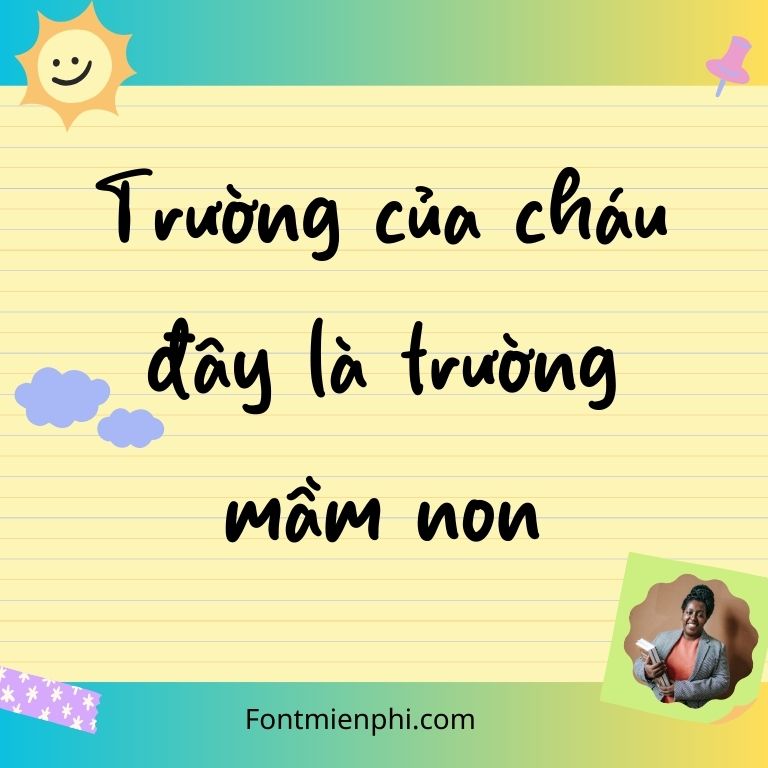
bộ Font Việt hóa VIP Burger Steak
Tải ngay bộ Font Việt hóa VIP Burger Steak siêu đẹp dành riêng cho dân thiết kế đồ họa. Đây là phông chữ hoàn hảo cho các dự án thiết kế logo, menu, và banner quảng cáo mảng F&B (ẩm thực, nhà hàng). Với đường nét mập mạp, vui nhộn và vô cùng cá tính, VIP Burger Steak đã được Việt hóa chuẩn xác, hỗ trợ gõ tiếng Việt có dấu đầy đủ không lỗi font. Khám phá và download miễn phí phông chữ độc đáo này để biến các thiết kế của bạn trở nên hấp dẫn, chuyên nghiệp và “ngon mắt” hơn
Khám Phá Sự Độc Đáo Của bộ Font Việt hóa VIP Burger Steak
Trong lĩnh vực thiết kế đồ họa, đặc biệt là mảng ẩm thực (F&B), việc lựa chọn đúng phông chữ đóng vai trò cực kỳ quan trọng trong việc kích thích vị giác và thu hút khách hàng. Nếu bạn đang tìm kiếm một kiểu chữ mang lại cảm giác ngon miệng, gần gũi và đầy sức sống, thì Font Việt hóa VIP Burger Steak chính là sự lựa chọn không thể bỏ qua.
1. Font VIP Burger Steak Là Gì?
VIP Burger Steak là một phông chữ hiển thị (display font) mang phong cách vui nhộn, mập mạp và đầy cá tính. Giống như tên gọi của mình, những đường nét của font chữ này gợi lên hình ảnh của những miếng bít tết dày dặn hay những chiếc burger đầy đặn, hấp dẫn. Nhận thấy tiềm năng ứng dụng to lớn của phông chữ này, các designer đã tiến hành Việt hóa hoàn chỉnh, giúp người dùng Việt Nam dễ dàng sáng tạo mà không lo lỗi dấu.
2. Ưu Điểm Nổi Bật Của Bản Việt Hóa
• Việt hóa chuẩn xác: Bộ font Việt hóa VIP Burger Steak đã được thêm đầy đủ các dấu câu tiếng Việt, tối ưu hóa khoảng cách (kerning) giữa các ký tự, đảm bảo hiển thị mượt mà trên mọi phần mềm thiết kế như Adobe Illustrator, Photoshop hay Canva.
• Thiết kế bắt mắt, ngộ nghĩnh: Các nét chữ bo tròn, đậm và không theo một quy chuẩn cứng nhắc nào giúp mang lại cảm giác thân thiện, trẻ trung và tràn đầy năng lượng.
• Khả năng thu hút thị giác cao: Với độ dày của nét chữ, font này cực kỳ phù hợp để làm tiêu đề lớn, tạo ấn tượng mạnh mẽ ngay từ cái nhìn đầu tiên.
3. Ứng Dụng Tuyệt Vời Trong Thiết Kế Đồ Họa
Bạn có thể sử dụng font VIP Burger Steak trong rất nhiều dự án khác nhau, tiêu biểu nhất là:
• Thiết kế mảng F&B: Làm phông chữ chủ đạo cho thiết kế menu, biển hiệu nhà hàng, quán ăn nhanh (fast food), tiệm bánh hay quán trà sữa.
• Thiết kế bao bì (Packaging): Tạo sự nổi bật cho nhãn mác sản phẩm, đặc biệt là các mặt hàng đồ ăn vặt, snack dành cho giới trẻ và trẻ em.
• Truyền thông & Quảng cáo: Rất thích hợp để làm typography cho các poster, banner khuyến mãi, bài đăng mạng xã hội cần sự tươi vui, nhí nhảnh.